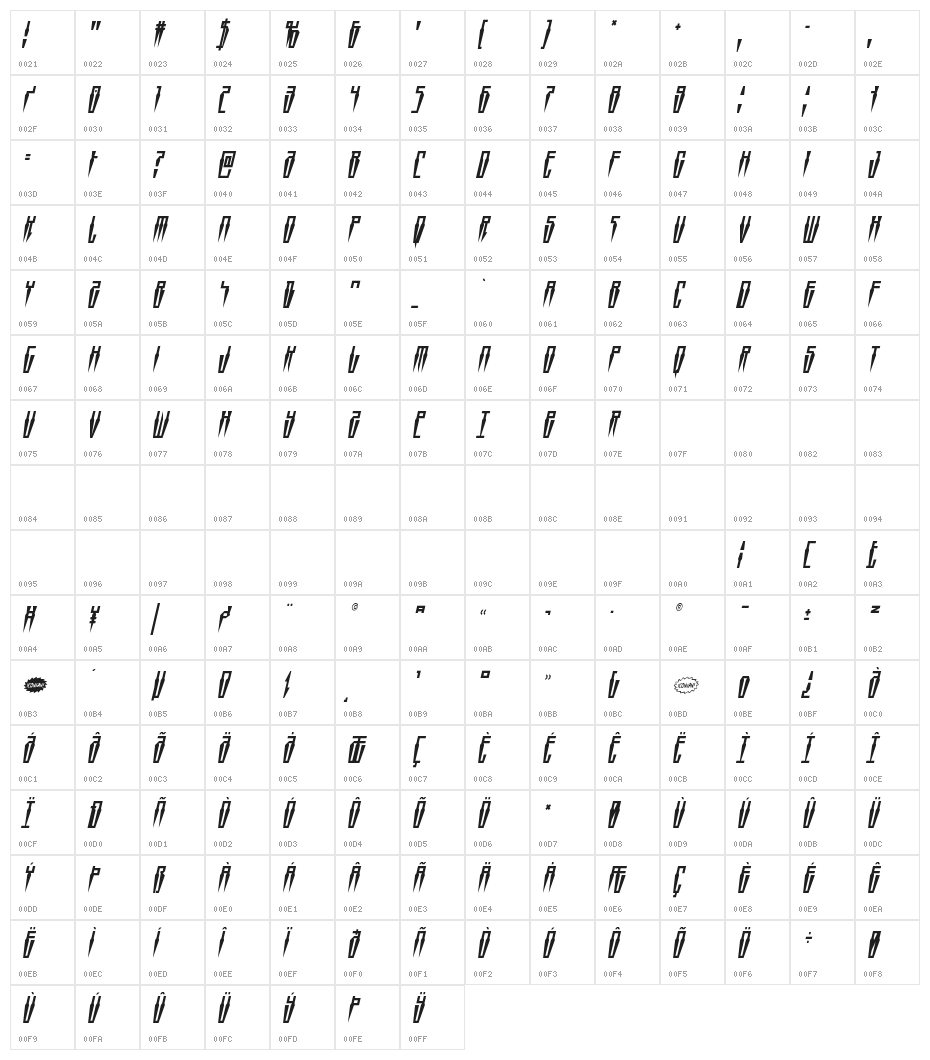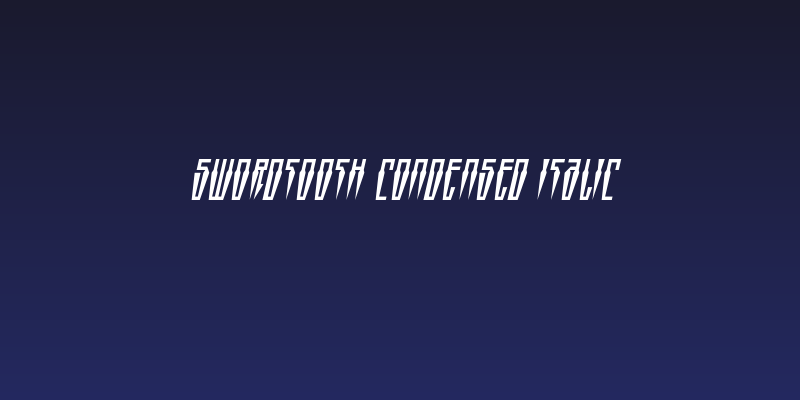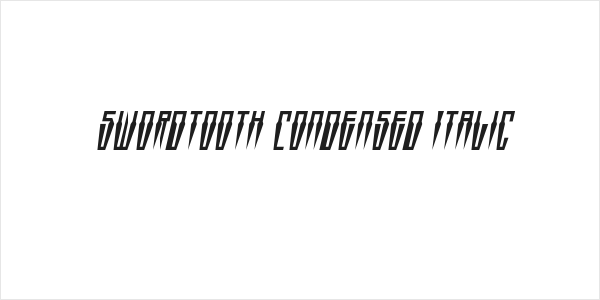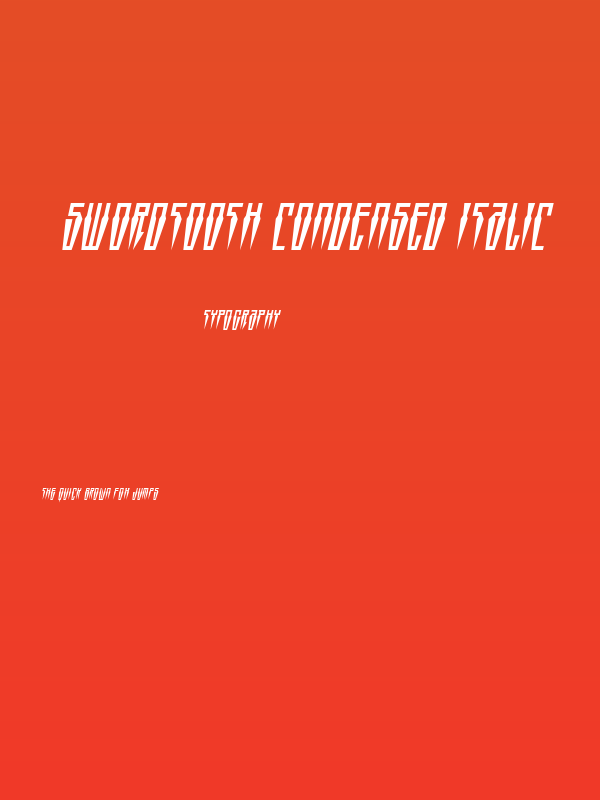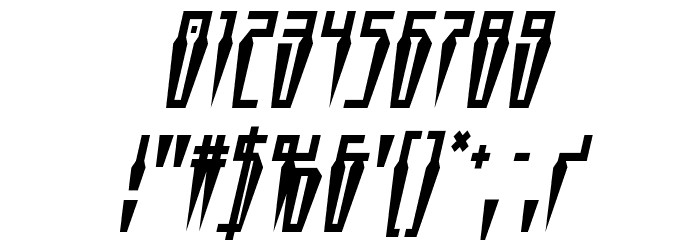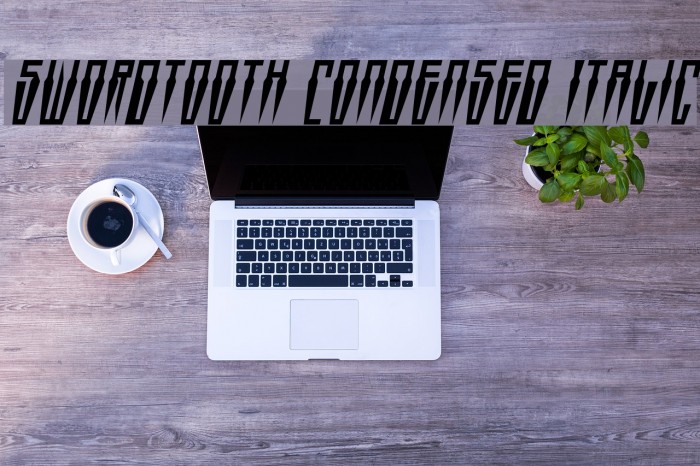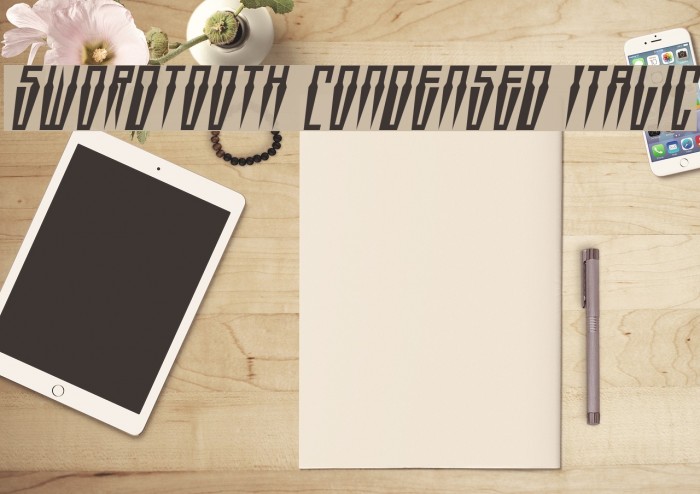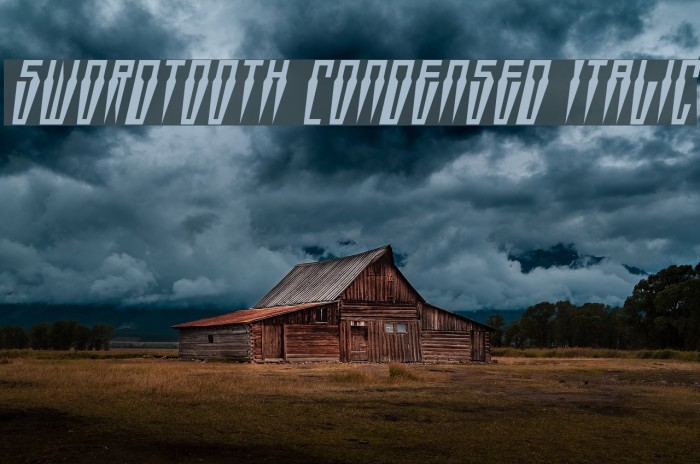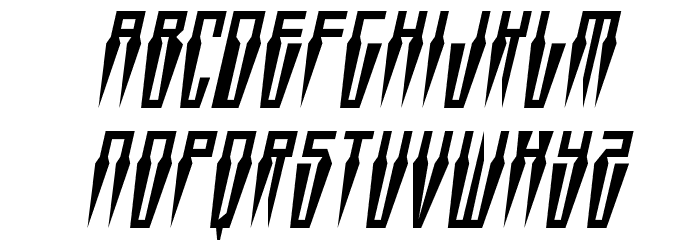
Swordtooth Condensed Italic Font
| Proyectos propuestos | Ideal for use in video game titles, movie posters, branding for extreme sports, or any project that requires a bold and aggressive visual impact. |